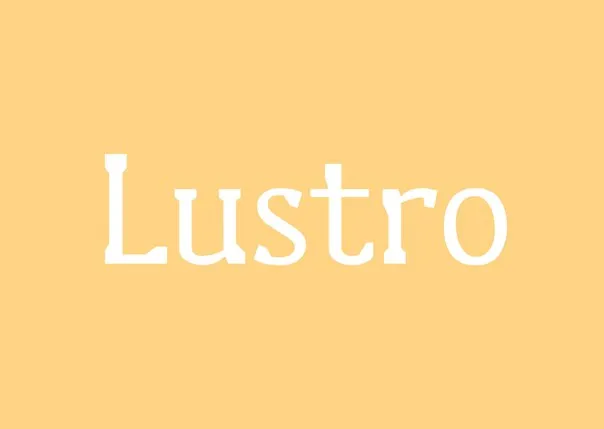
Lustro Font
A fonte ‘Lustro Font’ traz um ar sofisticado com sua tipografia serifada, mantendo uma personalidade forte e apresentando uma sensação ligeiramente retro que ainda não deixa de ser clássica. Seu design é puramente estilizado, criando uma aparência elegante e atraente em qualquer aplicação onde seja usada. Este tipo de fonte é particularmente apropriado para aplicações de mídia gráfica ou publicidade onde você precisa de uma tipografia que destaque seu conteúdo sem perder o aspecto legível. A inspiração vem da sofisticação dos anos 70, mas não é exagerada, mantendo-se coerente e facilmente leível em qualquer situação. Hamilton é o designer responsável por essa fonte, oferecendo um estilo único que combina modernidade com um toque nostálgico. Seja para criar logotipos, anúncios ou qualquer tipo de design gráfico que exija uma aparência sofisticada e atraente, ‘Lustro Font’ é uma escolha perfeita. Seu uso estilizado ainda preserva o nível de legibilidade necessário em um mundo de texto digital, tornando-a uma fonte versátil e segura para qualquer aplicação visual exigente.